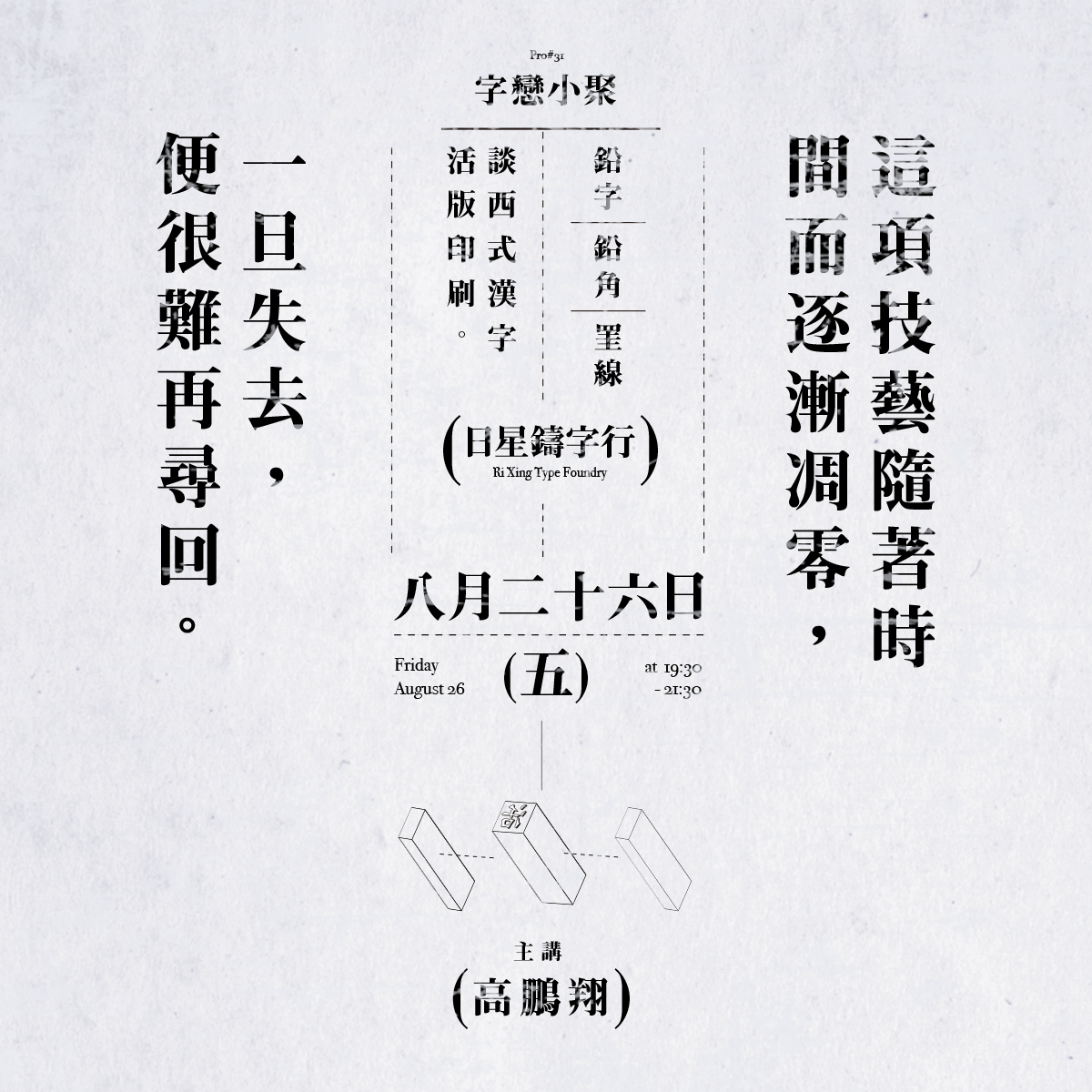
上個月的小聚,我們邀請到日星鑄字行的張老闆為我們分享初號楷體的復刻計畫,他將活字印刷的傳承與延續視為己任,努力於兩年間完成復刻計畫。復刻在即,傳承有望。
即使新一輩從未接觸活字印刷,卻能從長者口中延續活字的記憶;然而,若這項技藝隨著時間而逐漸凋零,一旦失去,便很難再尋回。活字排版的技法之所以彌足珍貴,在於紮實的鉛字、鉛角與罣線的運用,是年輕一輩的莘莘學子無法從電腦軟體中學到的排版技能,褪去活字老舊的衣裝,底下仍有著深厚功力的技藝靈魂,百年以來的精髓盡在活字工具的應用裡。
這一次,我們邀請到對活字印刷有著深度瞭解的高鵬翔老師,為我們介紹台灣西式的漢字活版印刷,從日治時期活字印刷被引進台灣後講起,在歷史脈絡中認識台灣的活字印刷,並且分享老師傅在進行活字排版時的傳統工法,為我們展現活字印刷的技術與工夫。